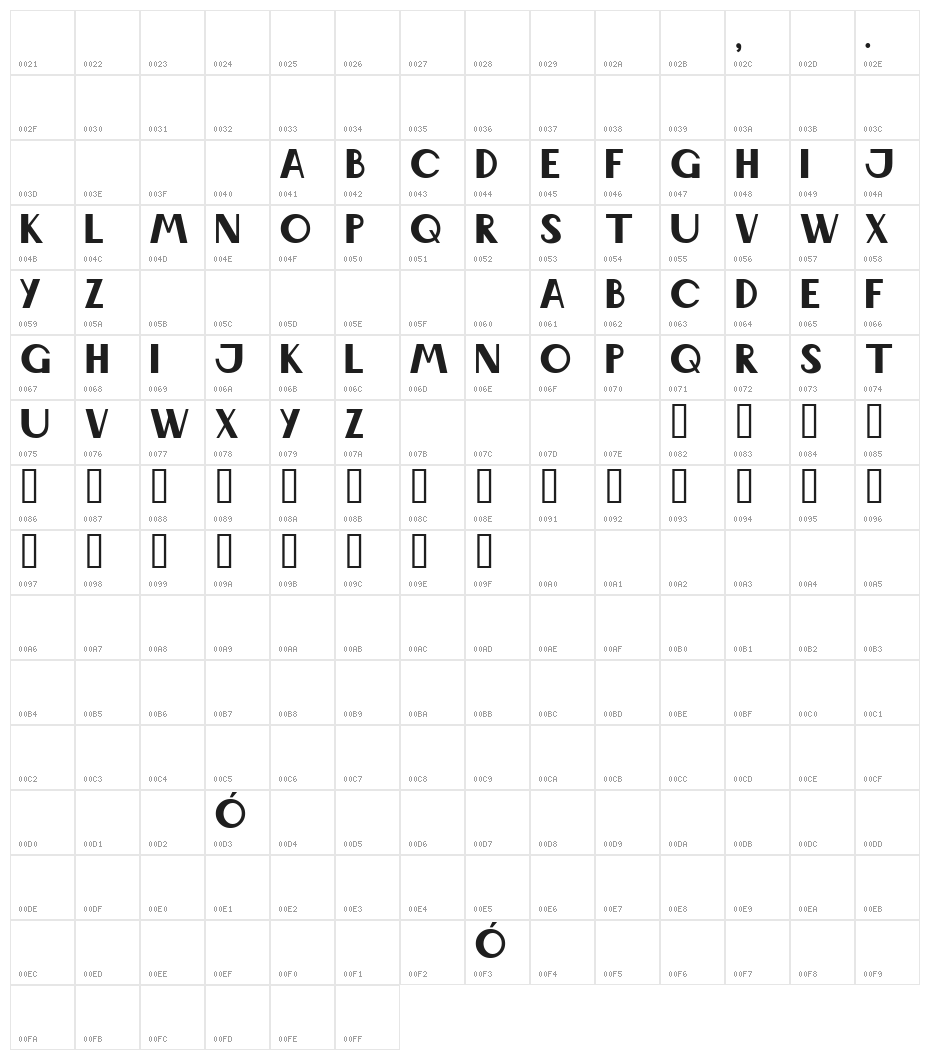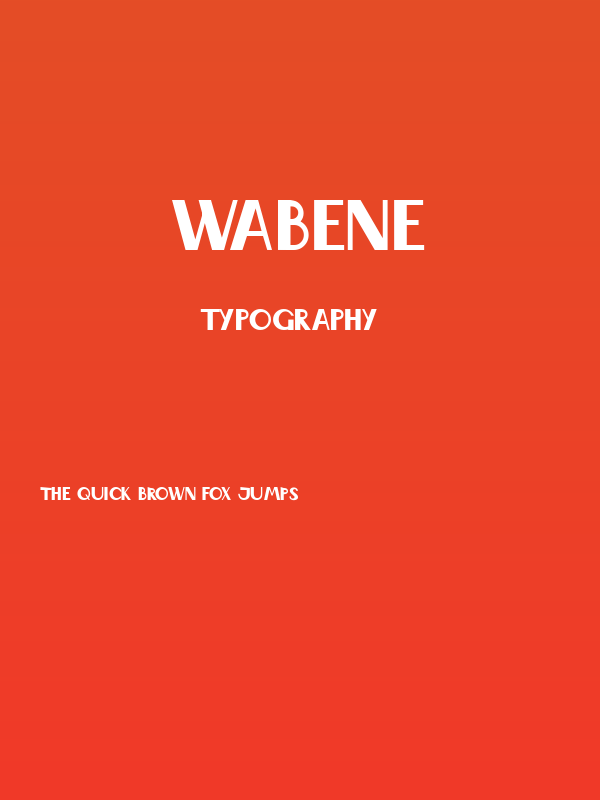
Wabene Font
✎ Retro
| Caso d'uso | Headlines, Logos, Branding |
| Progetti proposti | Ideal for branding, advertising, headlines, and digital media where a modern and bold statement is needed. |